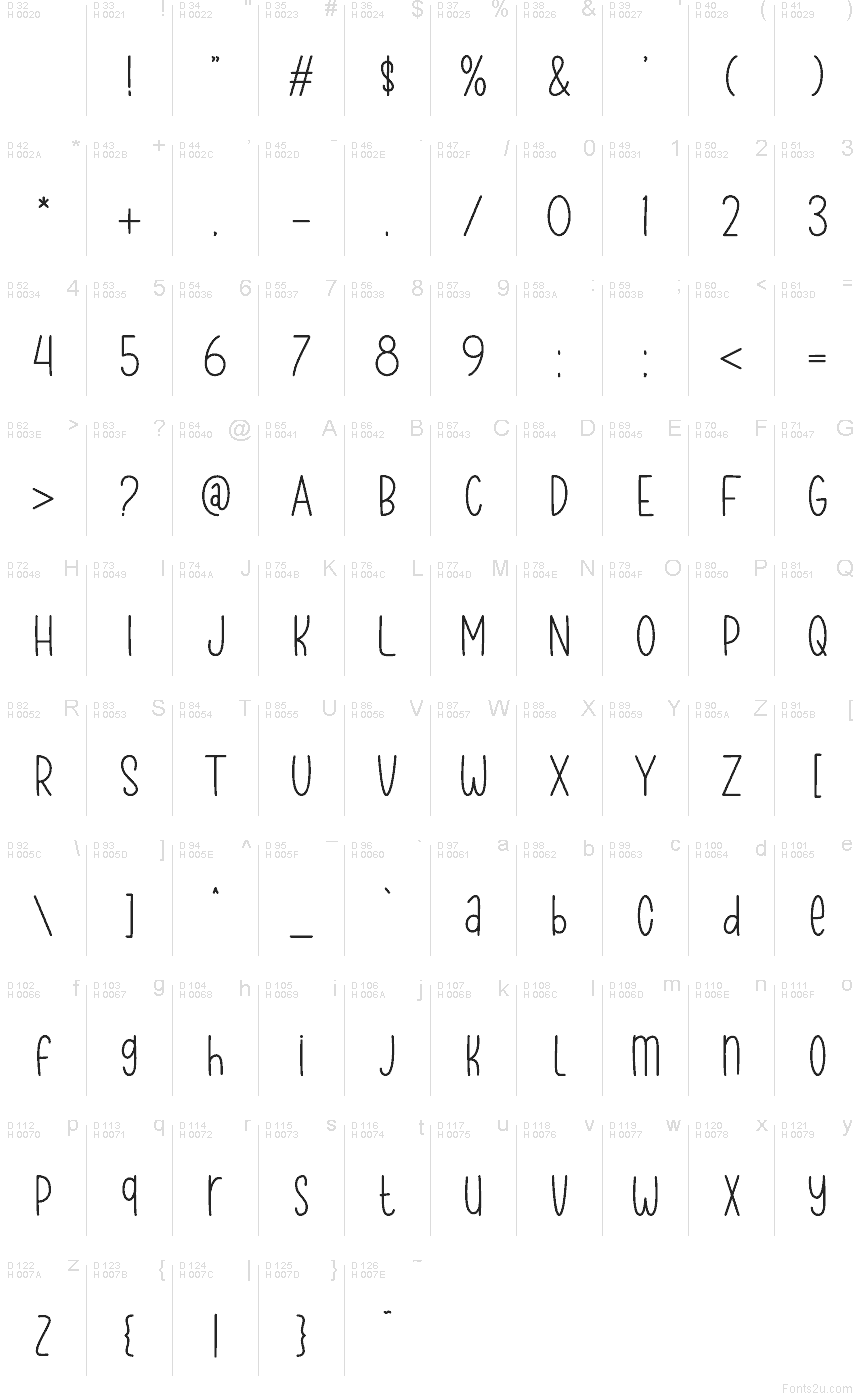
Garden House Sans od Madatype Studio je bezplatné ručně kreslené nadpisové písmo s vysokými, štíhlými písmeny a uvolněným, improvizovaným tvarem. Jeho nepravidelné jednorysové tahy, zaoblené ohyby a volné proporce připomínají rychlé nápisy fixem než uhlazenou typografii.
Zahrada a domov se hodí k jeho uvolněnému ručně vyrobenému stylu, což ho činí užitečným pro branding květinářství a trhové plakáty. Hodí se také pro kavárenské menu a řemeslné obaly. Na etiketách se může proměnit v načrtnutý obchodní štít namísto neutrálního textu.